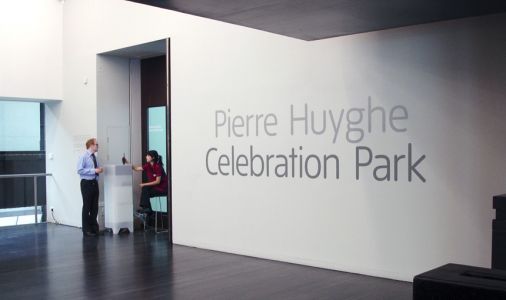
schrift gesucht / tate modern redesign
ich kann leider die schriftart des neuen tate modern
ausstellungsdesigns nicht identifizieren. kann mir jemand weiterhelfen?
die schrift heisst "tate" und wurde speziell fuer die tate galerie
angefertigt bzw. modifiziert. welche schrift als vorlage diente kann
ich dir aber leider auch nicht sagen ...